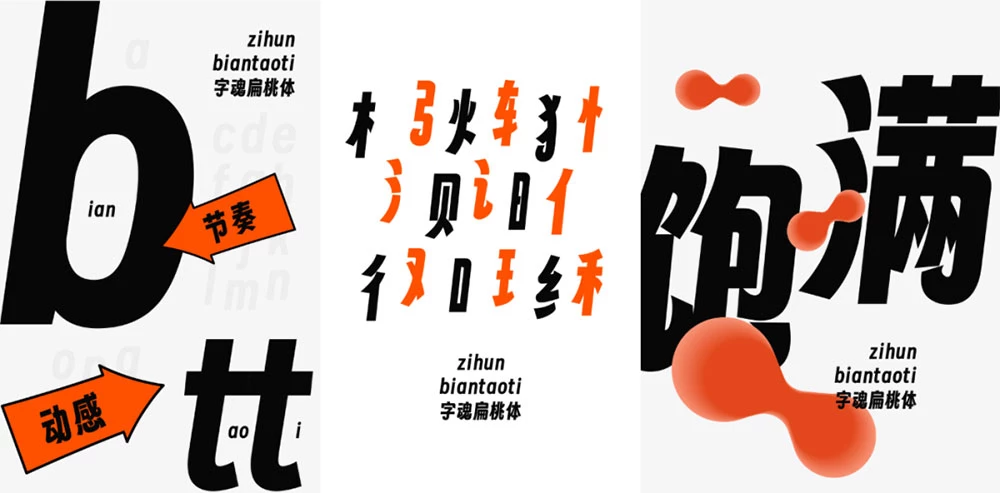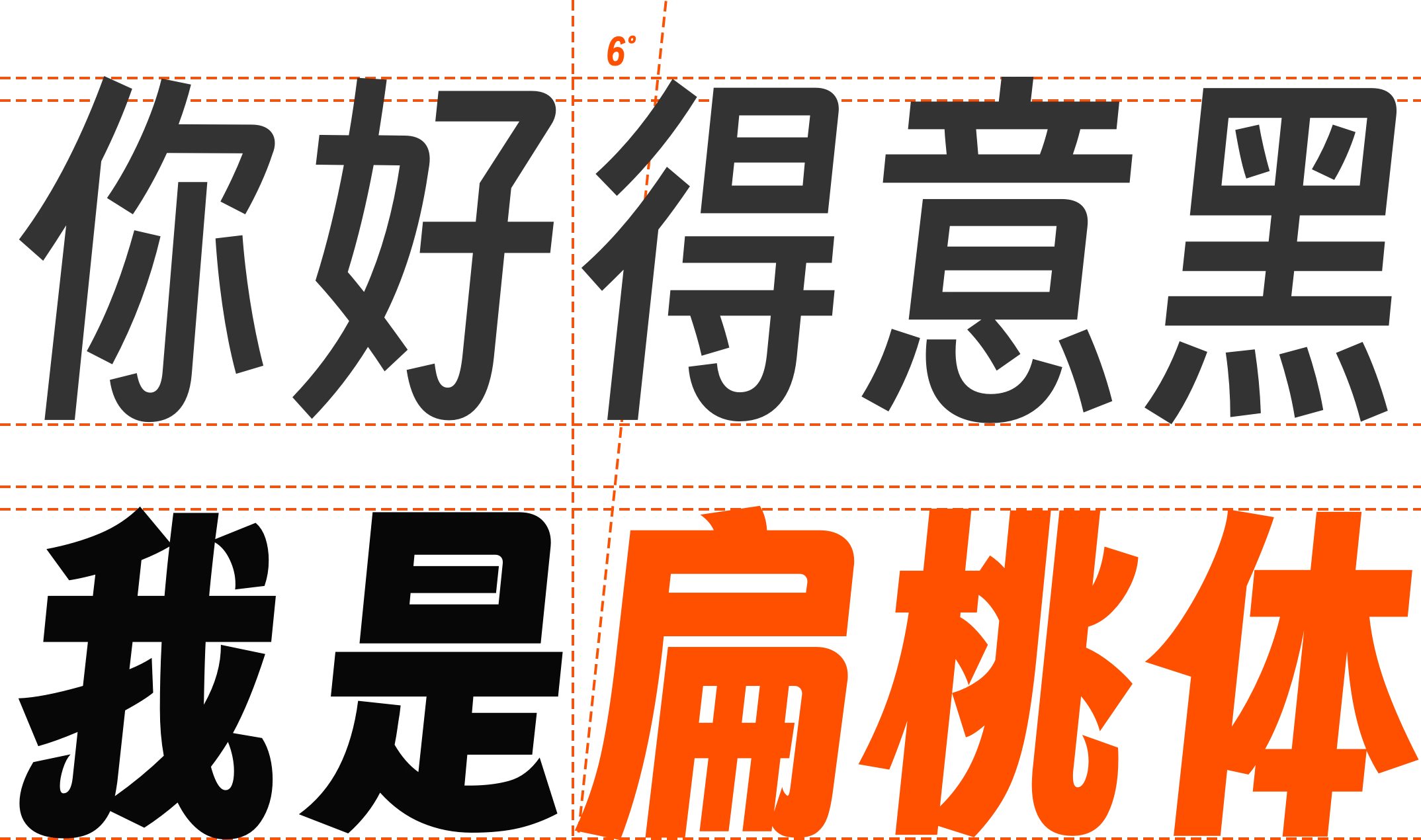
字魂扁桃体是字魂网基于得意黑进行二次创作后于2023年4月24日发布的又一款免费开源中文字体。两者都是黑体且带有一定的斜度,不同的是字魂扁桃体在得意黑的基础上对字重进行了加粗并略微加宽了字身,使其看起来更加厚重。同时,新加入了“喇叭口”的设计元素,让得意黑原本的圆角弧度更加明显,也充满了活力。
字魂扁桃体包含6767个中文字符,支持简体中文、英文字符、符号和数字。醒目独特的设计风格让其特别适合用于现代媒介、商业宣传、餐饮食品、运动户外、金融服务等场景。而且由于它是在得意黑的基础上再次创作所以也同样遵从OFL开源协议,个人和企业都可以免费商用且无需额外授权或标注原作者。